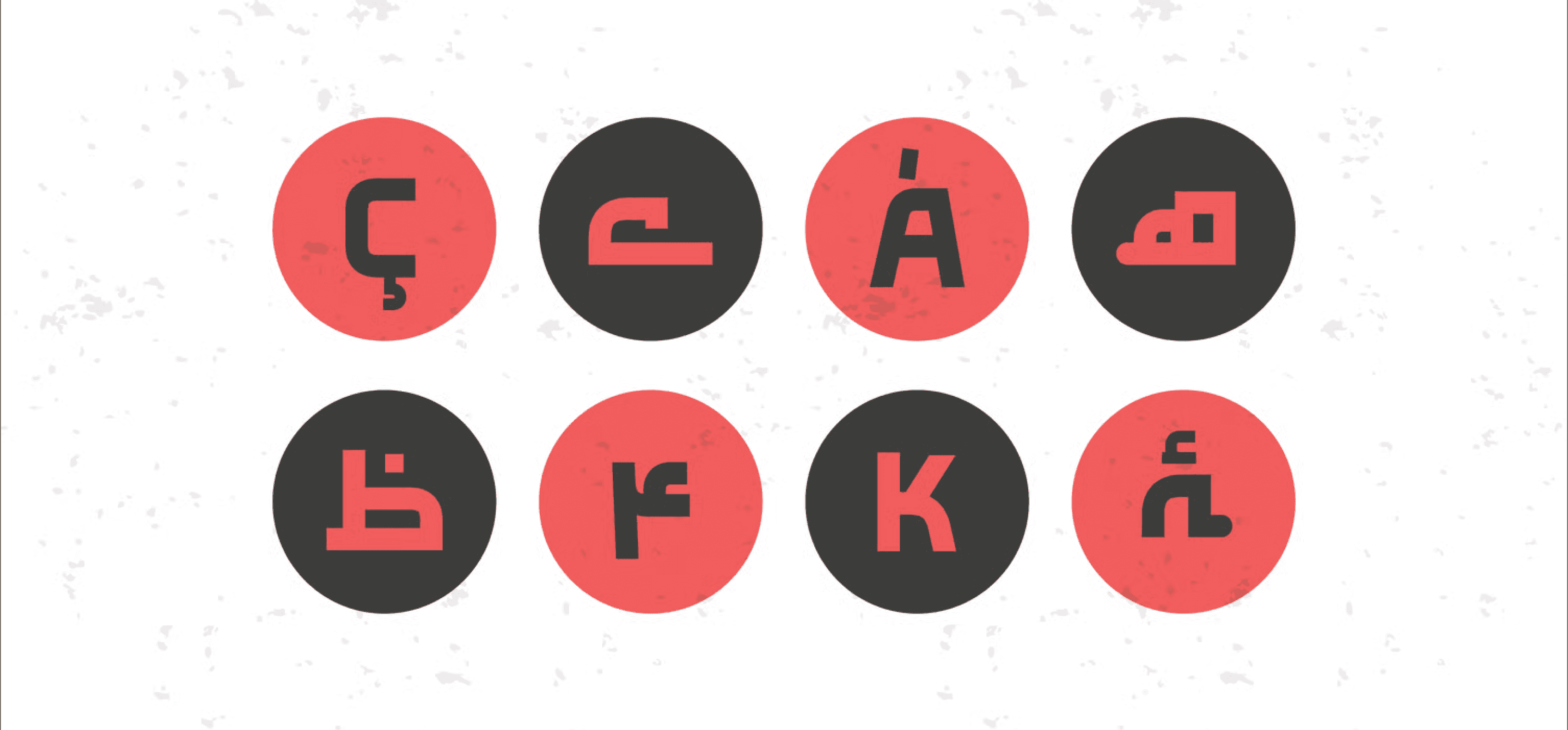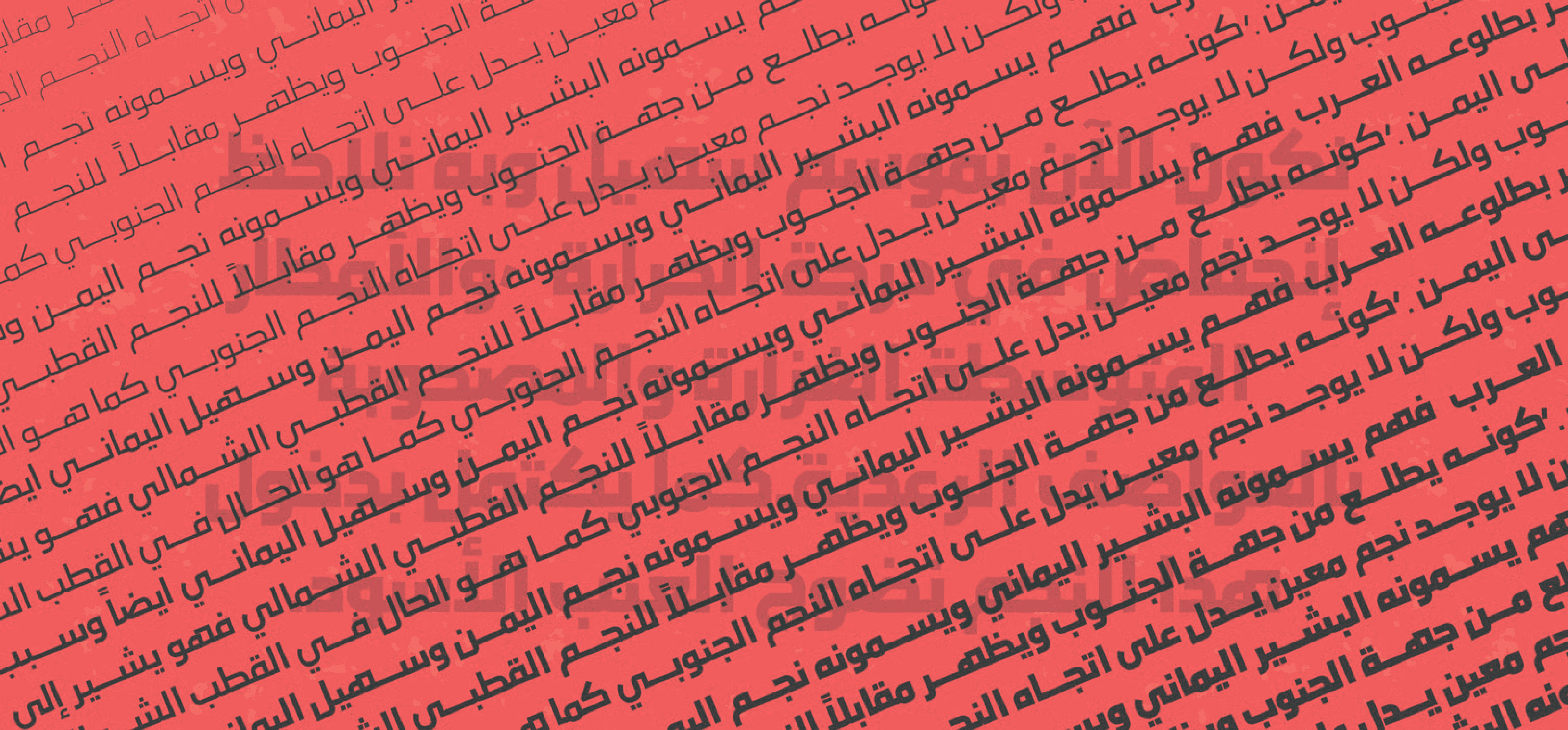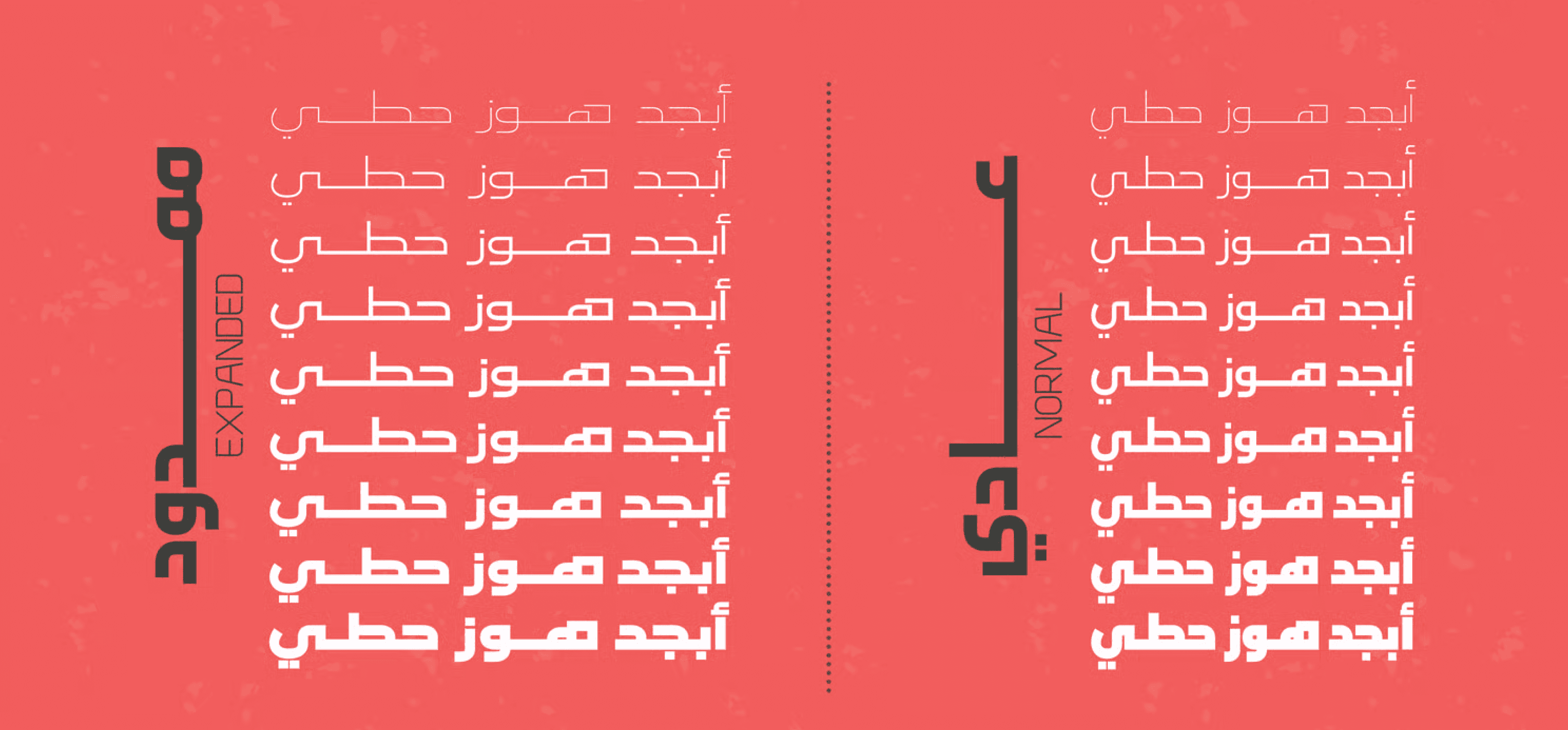
هي لغة متعددة اللغات تضم أكثر من خمس لغات ، بما في ذلك (العربية واللاتينية والفارسية والأردية) ذات قاعدة صلبة تتميز بالبساطة والحروف ذات الطابع الكوفي الهندسي.